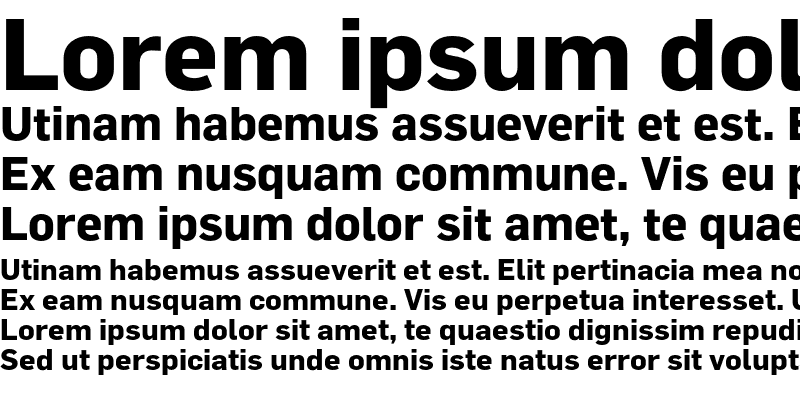
Tác giả: Mário Feliciano
Ngày phát hành: 2006
Phân loại: Độc đáo
Kiểu chữ: Sans-Serif
Độ dày: Thin, Light, Regular, Medium, Bold, Black
Flama Font Family là một bộ phông chữ đa dụng nổi bật, phù hợp với nhiều dự án thiết kế từ in ấn đến giao diện số. Được phát triển bởi liên minh giữa sự sáng tạo và tính năng kỹ thuật, Flama Font Family mang đến cảm giác hiện đại, sạch sẽ với các đường nét mượt mà và cân đối. Bộ font này thuộc bộ font chữ không chân không chỉ đáp ứng tốt nhu cầu trình bày văn bản mà còn tạo điểm nhấn độc đáo trong thiết kế đồ họa. Khám phá Flama Font Family để tìm thấy phong cách chữ viết lý tưởng cho dự án của bạn.